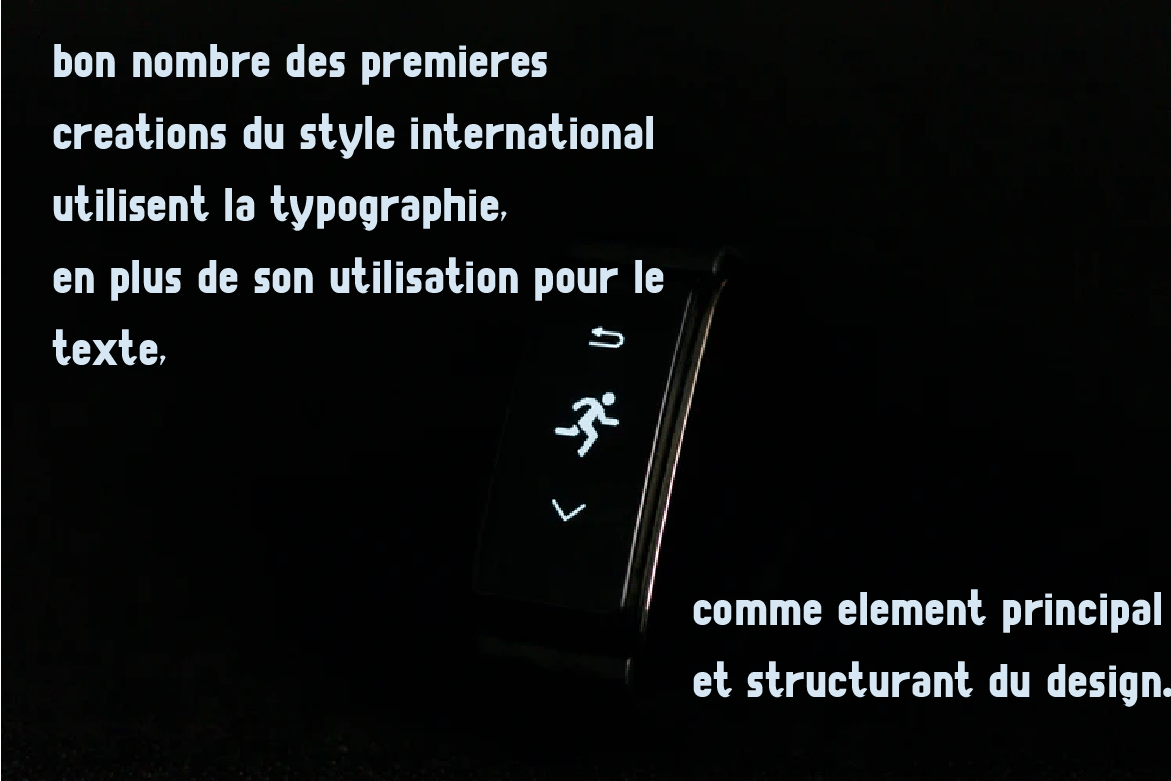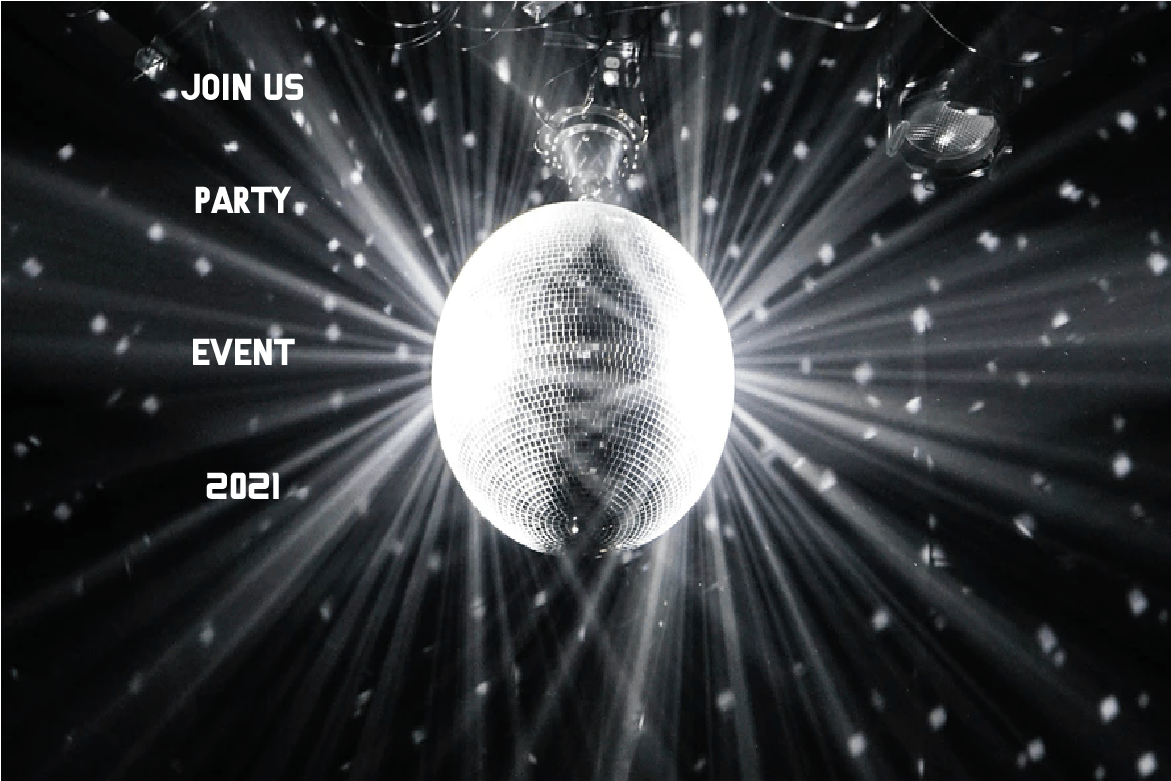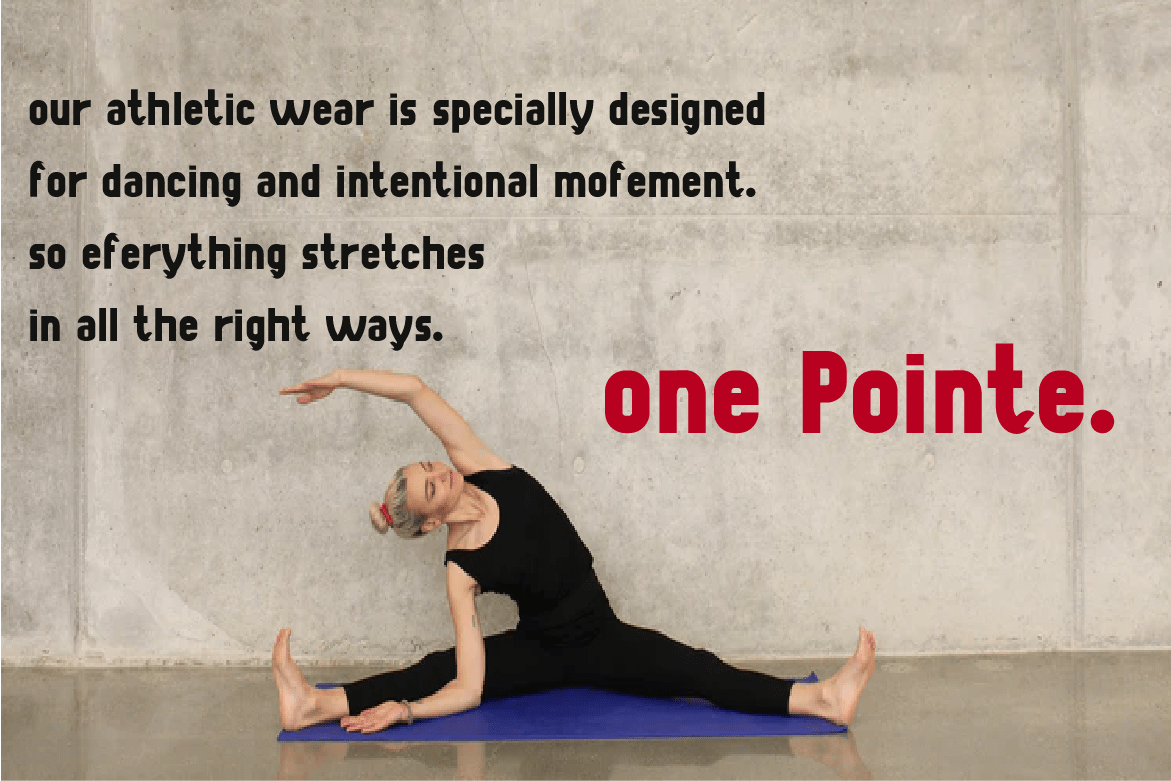
Zonular Font
Zonular Sans Serif Font
This font is inspired by the logos of popular magazines. Zonular adalah sebuah sebuah untaian fibrosa yang ssaling menghubungkan.
Zonular terbagi menjadi dua lapis, lapisan yang tipis, yang terhubung ke hialoid fossa dan lapisan yang lebih tebal yang berupa kumpulan serat zonular. font mode presentatif ini cocok untuk tata letak Modern, Elegan, kreatif, Profesional, dan unik.
Fashion, Business, Corporate, Photography, dan juga bisa digunakan untuk Portofolio. Bon nombre des premieres creations du style international utilisent la typographie, en plus de son utilisation pour le texte, comme element principal et structurant du design